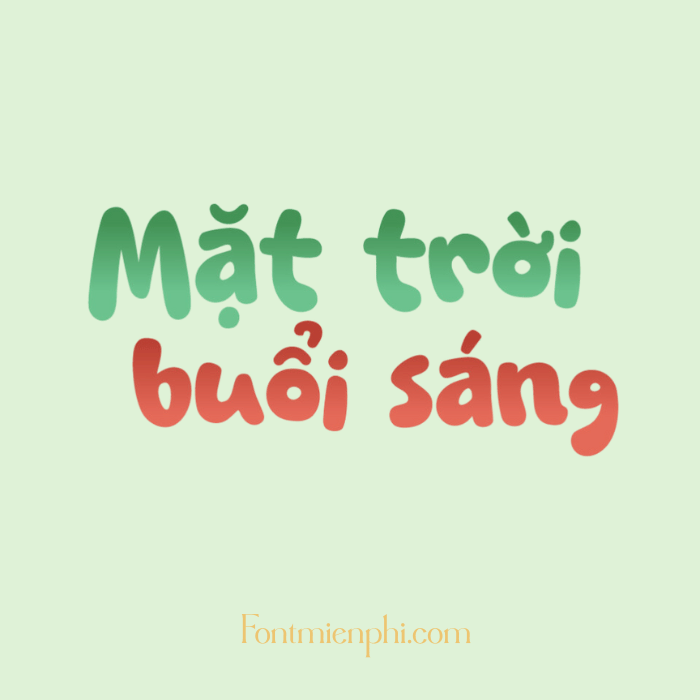
Font Việt hóa 1FTV VIP History of Wawa – Nét chữ độc đáo, sáng tạo
Font Việt hóa 1FTV VIP History of Wawa là bộ font chữ nghệ thuật độc đáo, được thiết kế dựa trên phong cách cổ điển kết hợp nét hiện đại. Với kiểu chữ uốn lượn, thanh thoát, font này phù hợp cho thiết kế poster, bìa sách, logo, hoặc các dự án sáng tạo cá nhân. Đặc biệt, font đã được Việt hóa hoàn chỉnh, hỗ trợ đầy đủ dấu tiếng Việt, giúp người dùng dễ dàng sử dụng trong mọi ấn phẩm.
Ưu điểm nổi bật:
✔️ Thiết kế độc quyền, phong cách vintage ấn tượng.